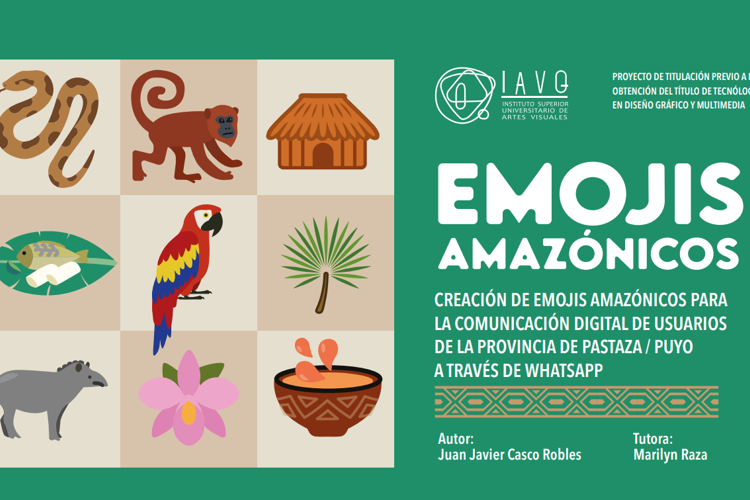
Emojis Amazonicos Font
Emojis Amazónicos es un proyecto de creación visual que brinda reprdentación social en emojis y pictogramas digitales de elementos culturales, naturales y rituales de la Amazonía ecuatoriana.
Busca preservar y difundir el patrimonio simbólico de los pueblos indígenas a través de un lenguaje gráfico global como los emojis, fusionando arte, tecnología, y educación con pertinencia cultural y memoria viva.